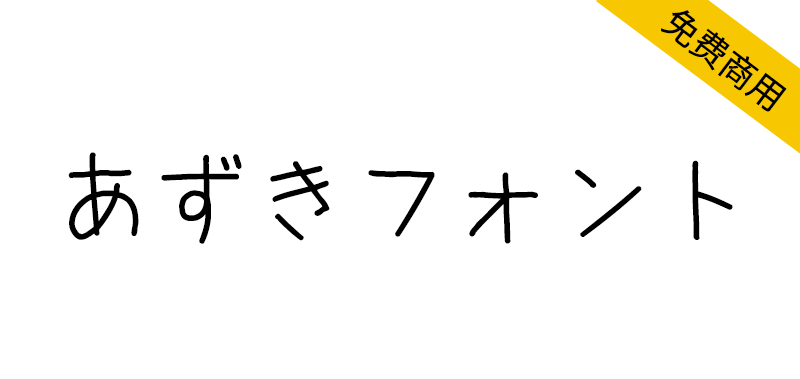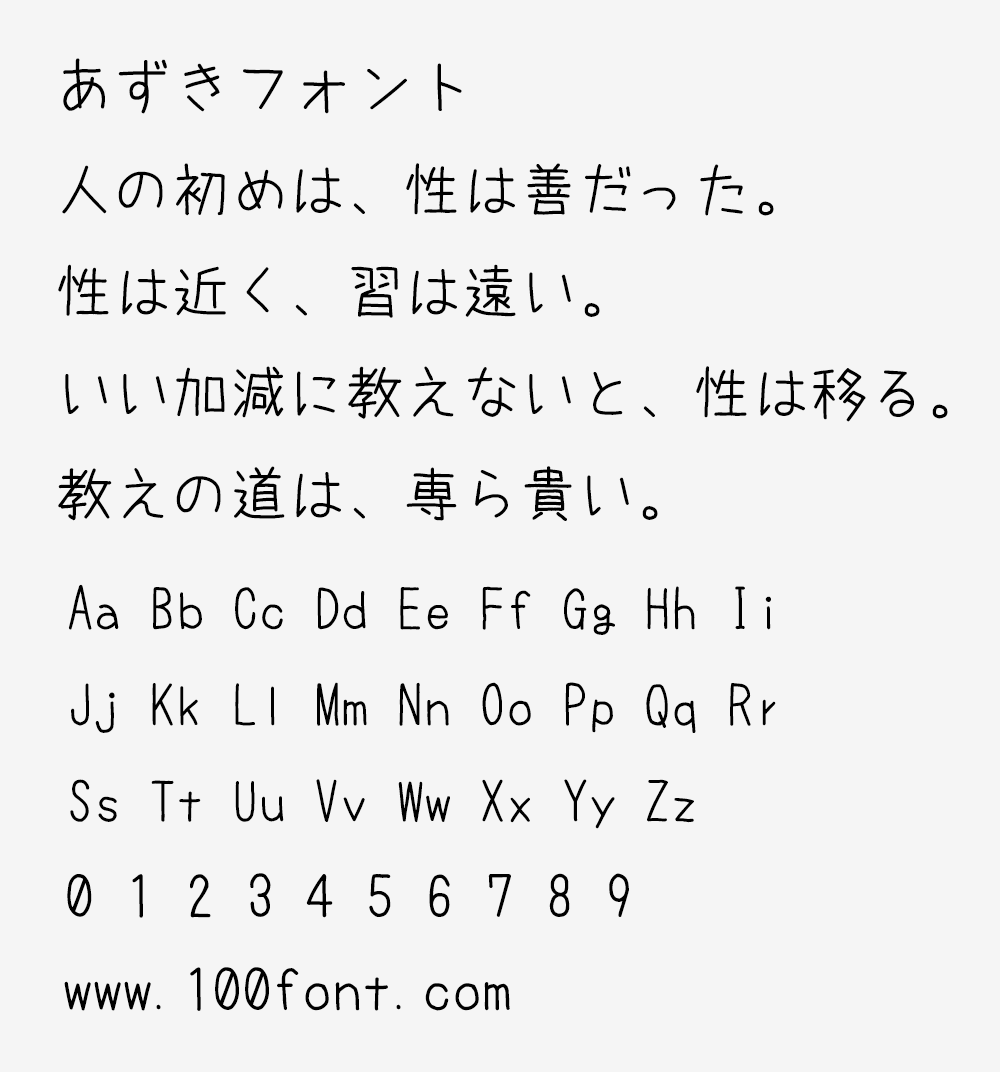
红豆字体(あずきフォント)这是原始手写字体,不太严肃也不太可爱的字体,建议使用抗锯齿,它很薄,可能不适合徽标等。
オリジナルの手書きフォントです。
「マジメすぎず、可愛すぎないフォント」
という地味な仕上がりになりました。
アンチエイリアス推奨です。
細い字なのでロゴ等には向いてないかもしれませんが、